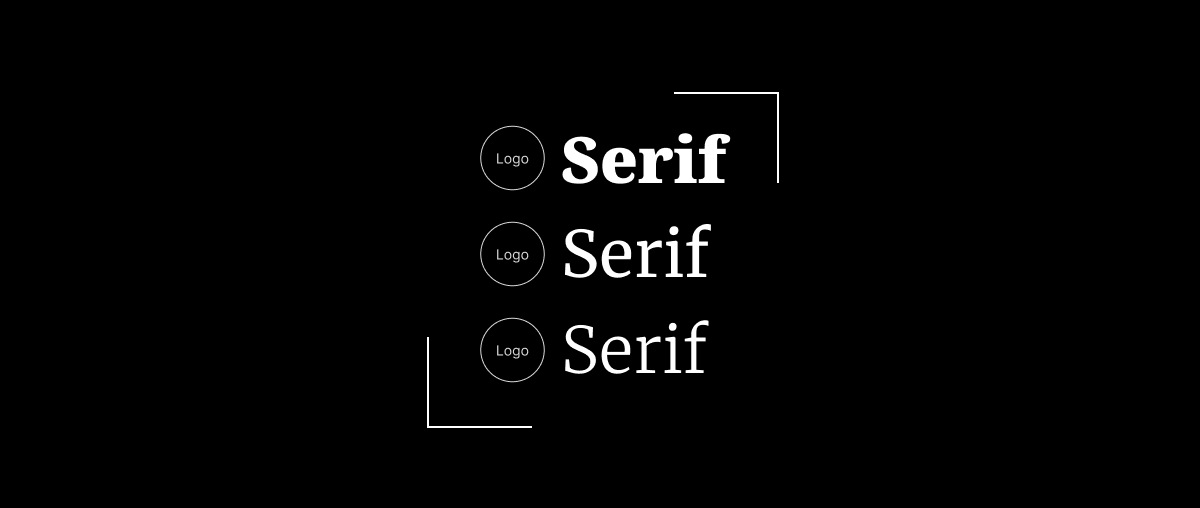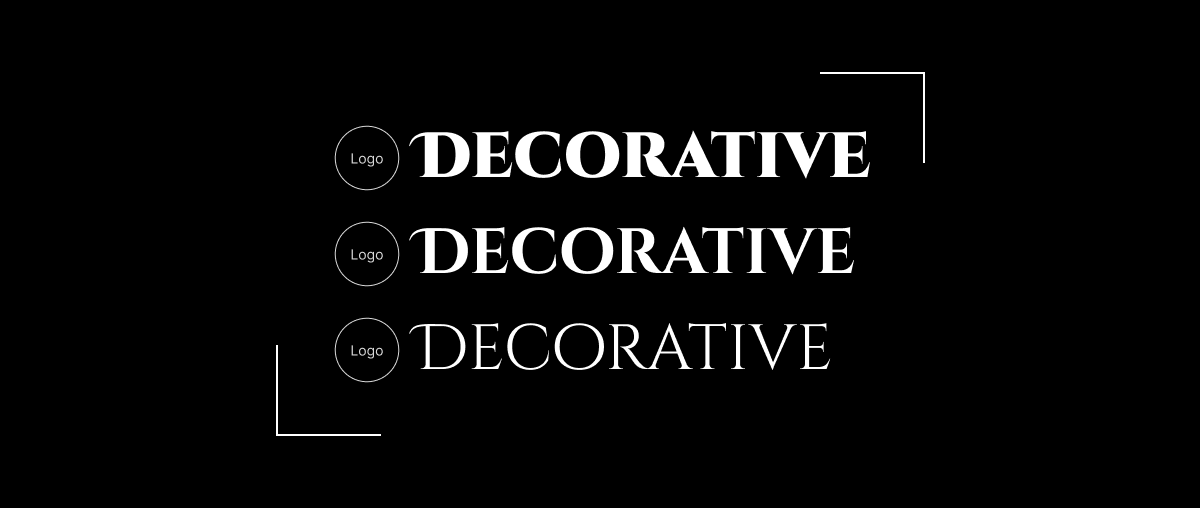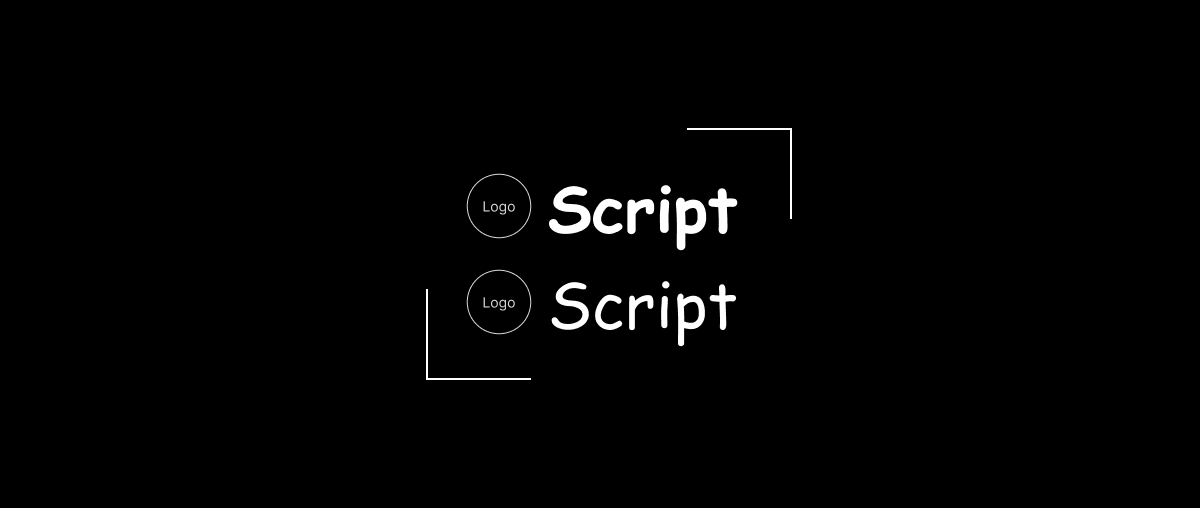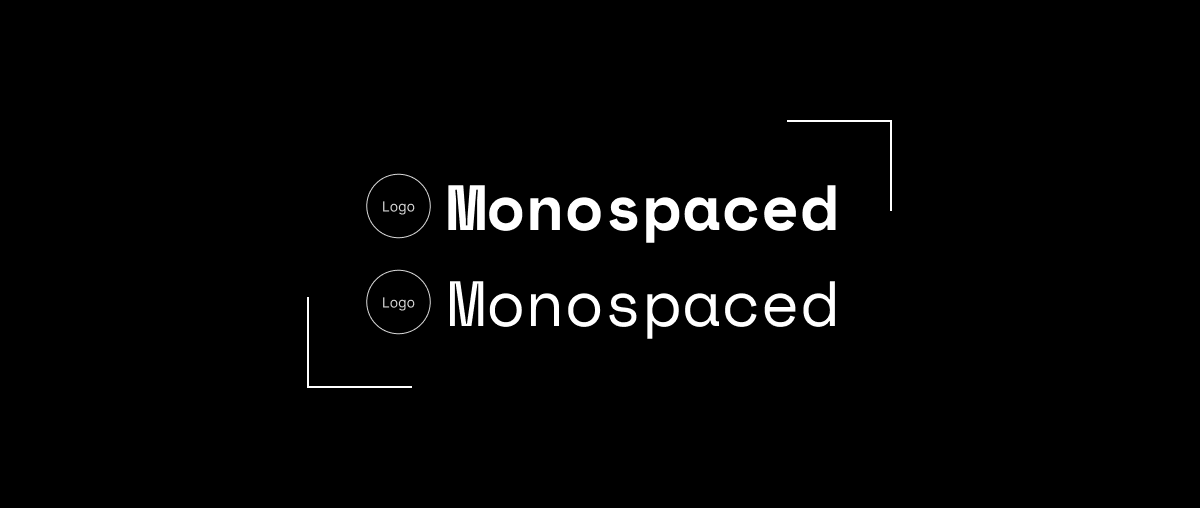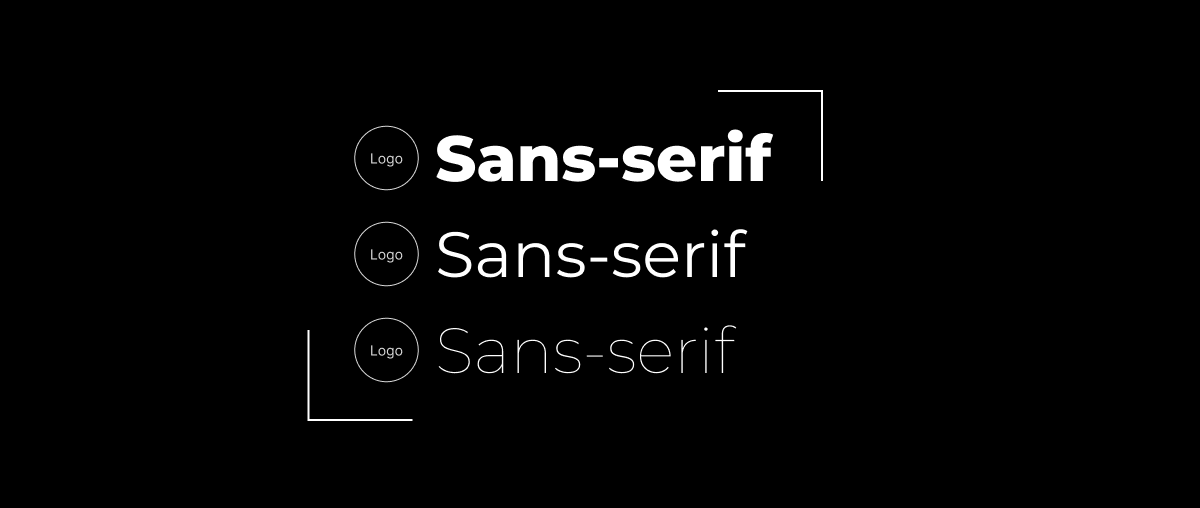
Typeface Là Gì? Những Điều Bạn Nên Biết Về Typeface
Phần lớn những người mới bắt đầu làm thiết kế đều mơ hồ về khái niệm typeface. Một kiểu chữ hoặc một tổ hợp các kiểu chữ giống nhau được gọi là typeface. Hãy cùng Terus tìm hiểu qua bài viết dưới đây.
I. Typeface là gì?
Typeface hay còn gọi là font family là một tập hợp các ký tự được thiết kế với phong cách thống nhất. Font face bao gồm các chữ cái, số, dấu chấm phẩy và các ký tự đặc biệt khác, cùng với các biến thể như chữ thường, chữ in hoa, chữ đậm, chữ nghiêng và các độ dày mỏng khác nhau.
Nó được sử dụng để tạo ra văn bản có tính thẩm mỹ và dễ đọc trong các ấn phẩm, thiết kế website và các ứng dụng khác. Typface có ý nghĩa khá rộng, bao gồm cả font vì typeface không bị hạn chế về định dạng và kích thước của chữ.
II. Tầm quan trọng của Typeface
Typeface đóng vai trò quan trọng trong thiết kế, ảnh hưởng đến nhiều khía cạnh như tính thẩm mỹ, khả năng truyền tải thông điệp, trải nghiệm người dùng và nhận diện thương hiệu. Dưới đây là một số lý do giải thích tầm quan trọng mà Terus muốn cung cấp cho bạn:
1. Truyền tải thông điệp
2. Thể hiện cá tính
3. Tạo cảm xúc
4. Hướng dẫn người đọc
5. Nhận diện thương hiệu
1. Truyền tải thông điệp
Typeface là yếu tố trực quan đầu tiên thu hút sự chú ý của người xem. Lựa chọn typeface phù hợp có thể giúp truyền tải thông điệp của bạn một cách hiệu quả. Chẳng hạn, Serif thường được sử dụng cho văn bản dài vì dễ đọc, trong khi Sans-serif phù hợp hơn cho tiêu đề và các đoạn văn bản ngắn.
2. Thể hiện cá tính
Typeface có thể thể hiện cá tính và phong cách của thiết kế. Typeface hiện đại, đơn giản có thể phù hợp cho một website công nghệ, trong khi typeface cổ điển, trang trọng có thể phù hợp hơn cho một thương hiệu cao cấp.
3. Tạo cảm xúc
Typeface có thể khơi gợi cảm xúc ở người xem. Typeface vui nhộn, sáng tạo có thể tạo cảm giác thích thú, trong khi typeface mạnh mẽ, dứt khoát có thể tạo cảm giác tin cậy.
4. Hướng dẫn người đọc
Typeface có thể được sử dụng để hướng dẫn người đọc chú ý đến những thông tin quan trọng trong thiết kế. Sử dụng typeface lớn, đậm cho tiêu đề và nhỏ hơn, thanh mảnh cho nội dung chính có thể giúp người đọc dễ dàng quét và nắm bắt thông tin.
5. Nhận diện thương hiệu
Typeface là một phần quan trọng của nhận diện thương hiệu. Lựa chọn kiểu chữ phù hợp và sử dụng nó một cách nhất quán có thể giúp tạo dựng hình ảnh thương hiệu mạnh mẽ và dễ nhận biết.
III. Một số loại Typeface
Typeface được phân loại thành các nhóm chính dựa trên đặc điểm hình dạng và tính năng của chúng. Dưới đây là một số loại phổ biến mà Terus muốn giới thiệu đến bạn:
1. Sans-serif
2. Serif
3. Script
4. Decorative
5. Mimicry
6. Monospaced
7. Fantasy Decoration
1. Sans-serif
Đây là loại chữ không có chân. Hầu hết các font chữ được sử dụng là Verdana, Arial, Tahoma, Gill Sans, Franklin Gothic, Futura và Univers. Vì nó đơn giản nên kiểu chữ này dễ nhận biết. Nhờ vào những tiến bộ đáng kể trong lĩnh vực này và sự phát triển của internet, loại chữ này đã được sử dụng khá phổ biến và rộng rãi vì nó dễ đọc, phù hợp với nhiều trường hợp và có nhiều kích thước.
Sans-serif
Sans-serif cũng được đánh giá cao vì nó có thể truyền đạt thông điệp bằng cách sử dụng các phương pháp trang trí tượng hình hoặc nhấn mạnh.
Các nhà thiết kế thường sử dụng sự đơn giản của kiểu chữ này để tạo ra một xu hướng mới giúp đảm bảo rằng tác phẩm của họ tối giản. Sự tối giản trong cách trang trí bằng kiểu chữ Sans-serif sẽ giúp tác phẩm trở nên thu hút hơn và độc đáo hơn.
2. Serif
Một loại chữ có chân được gọi là Serif. Có một số loại chữ phổ biến nhất, chẳng hạn như Times New Roman, Cambria, Book Antiqua, Georgia và Bookman, có kiểu chữ khá giống với Sans-serif ở chân và viền đỉnh của mỗi ký tự. Các nhà thiết kế chuyên nghiệp và những người sử dụng email sử dụng Serif.
Serif
Serif cũng rất tốt cho các loại văn bản trang trọng, thư từ về thương mại, thông điệp quảng cáo và các phương tiện truyền thông khác vì kiểu chữ này phổ biến và chuyên nghiệp.
Slab Serif là một font con của kiểu chữ Serif. Font này có dạng hình khối khá cứng cáp và các ký tự trong nó không bị lẫn nhau. Các dòng tiêu đề nên có kiểu chữ dày.
3. Script
Đây là kiểu chữ được tạo ra bởi các mẫu chữ viết tay. Nó thường được sử dụng trong các loại văn bản thể hiện cảm xúc của người viết hoặc giúp người đọc cảm thấy đồng cảm với họ.
Script
Các font chữ được sử dụng phổ biến trong typeface bao gồm Mistral, Comic Sans, Lucida Handwriting, Monotype, Brush Script và các font khác. Kiểu chữ này từ những kiểu chữ biết từ phấn đến những kiểu chữ nghệ thuật và tao nhã. Đây là loại chữ được sử dụng khá phổ biến để mang lại cho người xem cảm giác tinh tế và hài hước.
Văn bản trang trọng và thân mật thường có script. Tuy nhiên, kiểu chữ này không thể thể hiện được quyền lực hay uy tín của một văn bản, vì vậy chỉ nên sử dụng nó trong các văn bản mang tính tổ chức.
4. Decorative
Đây là kiểu chữ khá giống Serif vì nó có tính trang trí tự nhiên. Các nhà thiết kế thường sử dụng typeface để tạo ra các đối tượng trang trí hoặc làm điểm nhấn cho các biểu diễn của họ. Ngoài ra, kiểu chữ này rất phổ biến khi sử dụng các loại hình ảnh hoặc cảm xúc cho một số thể loại hoặc cột mốc thời gian cụ thể.
Decorative
Tuy nhiên, Terus khuyên bạn đừng sử dụng kiểu chữ này trong báo cáo kinh doanh hoặc tin tức vì nó có thể làm giảm giá trị của nội dung. Ngoài ra, bạn nên lựa chọn kỹ lưỡng khi sử dụng bất kỳ kiểu chữ nào cho không gian thiết kế.
5. Mimicry
Đây là loại chữ trang trí được tạo ra bằng cách nhái lại các loại chữ khác nhau. Tiếng Trung, tiếng Hàn và tiếng Ấn là những ví dụ. Cảm giác ngoại ngữ trong thiết kế thường được tạo ra bằng cách sử dụng các loại chữ này.
6. Monospaced
Đây là kiểu chữ có độ rộng của các con chữ bằng nhau, mang lại cảm giác đều đặn và mũm mĩm. Nó cũng mang lại cảm giác khá hay ho. Monospace và lucida là những ví dụ về font chữ này.
Monospaced
7. Fantasy Decoration
Đây có thể được coi là kiểu chữ có hình thù đặc biệt nhất vì nó thường có hình dạng như con người, đồ vật, nhân vật hoạt hình hoặc hoa văn.
IV. Cách sử dụng typeface phù hợp
Typeface đóng vai trò quan trọng trong thiết kế, ảnh hưởng đến tính thẩm mỹ, khả năng truyền tải thông điệp và trải nghiệm người dùng. Sử dụng kiểu chữ đúng cách giúp bạn tạo ra những thiết kế đẹp mắt, thu hút và hiệu quả. Terus sẽ mang đến cho bạn một số nguyên tắc cơ bản để sử dụng hiệu quả:
1. Lựa chọn typeface phù hợp
2. Sử dụng tối đa 2-3 typeface trong cùng một thiết kế
3. Sử dụng các biến thể của typeface
4. Chú ý đến khoảng cách và bố cục
5. Sử dụng typeface chất lượng cao
6. Kiểm tra typeface trên nhiều thiết bị
7. Cập nhật xu hướng typeface
1. Lựa chọn typeface phù hợp
Xác định mục đích sử dụng: Bạn muốn thiết kế gì? Website, áp phích, logo, sách báo? Mục đích sử dụng sẽ ảnh hưởng đến loại typeface phù hợp.
Xác định đối tượng mục tiêu: Ai là người sẽ xem thiết kế của bạn? Độ tuổi, sở thích, trình độ của họ là gì? Hiểu rõ đối tượng mục tiêu giúp bạn chọn typeface phù hợp với thị hiếu và khả năng tiếp nhận của họ.
Xác định thông điệp muốn truyền tải: Bạn muốn truyền tải thông điệp gì qua thiết kế? Thông điệp vui nhộn, trang trọng, hay hiện đại? Lựa chọn typeface phù hợp với thông điệp sẽ giúp tăng hiệu quả truyền tải.
2. Sử dụng tối đa 2-3 typeface trong cùng một thiết kế
Việc sử dụng quá nhiều typeface có thể khiến thiết kế trở nên rối mắt và khó đọc. Nên sử dụng tối đa 2-3 loại cho một thiết kế, kết hợp hài hòa để tạo sự cân bằng và thống nhất.
3. Sử dụng các biến thể của typeface
Hầu hết các typeface đều có các biến thể như chữ thường, chữ in hoa, chữ đậm, chữ nghiêng và các độ dày mỏng khác nhau. Sử dụng các biến thể này một cách hợp lý giúp tạo điểm nhấn, phân chia cấp bậc thông tin và tăng hiệu quả đọc.
4. Chú ý đến khoảng cách và bố cục
Khoảng cách giữa các ký tự, giữa các dòng chữ và khoảng cách lề trang ảnh hưởng đến khả năng đọc và tính thẩm mỹ của thiết kế. Hãy đảm bảo các khoảng cách được sắp xếp hợp lý, tạo sự thoải mái cho mắt người đọc.
5. Sử dụng typeface chất lượng cao
Sử dụng typeface chất lượng cao giúp đảm bảo hình ảnh rõ nét, không bị vỡ hoặc biến dạng. Tránh sử dụng kiểu chữ miễn phí có chất lượng thấp hoặc không rõ nguồn gốc.
6. Kiểm tra typeface trên nhiều thiết bị
Thiết kế của bạn sẽ được hiển thị trên nhiều thiết bị khác nhau như máy tính, điện thoại, máy tính bảng. Hãy kiểm tra typeface trên nhiều thiết bị để đảm bảo hiển thị chính xác và đẹp mắt trên mọi màn hình.
Kiểm tra typeface trên nhiều thiết bị
7. Cập nhật xu hướng typeface
Ngành thiết kế luôn thay đổi và phát triển. Hãy cập nhật xu hướng typeface mới để tạo ra những thiết kế hiện đại và thu hút.
Nhìn chung, Typeface là một công cụ thiết kế mạnh mẽ có thể giúp bạn truyền tải thông điệp, thể hiện cá tính, tạo cảm xúc, hướng dẫn người đọc và xây dựng nhận diện thương hiệu. Hãy dành thời gian để tìm hiểu về các loại typeface khác nhau và sử dụng chúng một cách hiệu quả để tạo ra những thiết kế đẹp mắt, thu hút và truyền tải thông điệp hiệu quả.
V. Tổng kết
Bài viết là các thông tin về Typeface và những điều bạn nên biết về Typeface mà Terus muốn gửi đến cho quý đơn vị đang hợp tác đến Terus và bạn bè doanh nghiệp của Terus.
Hi vọng bài viết có thể giúp ích được cho bạn, cảm ơn bạn đã đọc hết bài viết.
Nếu bạn có bất cứ yêu cầu gì về Terus có thể liên hệ tại đây nhé!
Theo dõi Terus tại:
FAQ – Giải đáp thắc mắc về Typeface
1. Làm thế nào để kết hợp nhiều typeface trong một thiết kế mà vẫn đảm bảo tính thẩm mỹ?
Việc kết hợp nhiều typeface có thể tạo điểm nhấn và sự đa dạng cho thiết kế. Tuy nhiên Terus muốn lưu ý rằng một số nguyên tắc để đảm bảo tính thẩm mỹ:
• Chọn typeface có cùng phong cách hoặc tương đồng nhau.
• Sử dụng tỷ lệ phân cấp: Sử dụng kiểu chữ có kích thước và độ dày mỏng khác nhau để tạo điểm nhấn và phân chia cấp bậc thông tin.
• Hạn chế số lượng: Nên sử dụng tối đa 2-3 typeface trong cùng một thiết kế để tránh gây rối mắt.
• Chú ý đến màu sắc: Sử dụng màu sắc phù hợp để tạo sự hài hòa giữa các.
2. Nên sử dụng typeface nào cho logo?
Lựa chọn typeface cho logo phụ thuộc vào nhiều yếu tố như ngành nghề, đối tượng mục tiêu, thông điệp thương hiệu. Tuy nhiên, ở phần này Terus cũng có một số lưu ý chung khi chọn typeface cho logo:
• Đơn giản, dễ đọc: Logo cần dễ đọc và ghi nhớ, tránh sử dụng typeface quá phức tạp hoặc cầu kỳ.
• Phù hợp với ngành nghề: Serif có thể phù hợp cho thương hiệu luật sư, trong khi Sans-serif phù hợp cho thương hiệu công nghệ.
• Thể hiện cá tính thương hiệu: Logo cần thể hiện được cá tính và thông điệp của thương hiệu.
• Dễ ứng dụng: Logo cần dễ ứng dụng trên nhiều phương tiện khác nhau như in ấn, website, mạng xã hội.
3. Xu hướng typeface nào đang thịnh hành trong thiết kế hiện nay?
Dưới đây, Terus sẽ giới thiệu đến bạn một số xu hướng typeface phổ biến hiện nay:
• Sans-serif hiện đại: Loại này đơn giản, dễ đọc và phù hợp với thiết kế website và giao diện ứng dụng.
• Serif cổ điển: Loại này mang lại cảm giác sang trọng, tinh tế và có thể phù hợp cho logo hoặc ấn phẩm cao cấp.
• Viết tay: Loại này tạo cảm giác gần gũi, thân thiện và có thể phù hợp cho thương hiệu hướng đến đối tượng trẻ.
• Vui nhộn, sáng tạo: Loại này thu hút sự chú ý và có thể phù hợp cho thương hiệu muốn thể hiện sự trẻ trung, năng động.
4. Sự khác biệt giữa Typeface và Font?
Typeface là thiết kế tổng thể của một tập hợp ký tự, bao gồm các yếu tố như kiểu dáng, đường nét, tỷ lệ và khoảng cách giữa các ký tự.
Font là một tập tin kỹ thuật số chứa các ký tự của một typeface ở một định dạng cụ thể, ví dụ như TrueType OpenType (OTF), Web Open Font Format (WOFF) hoặc Scalable Vector Graphics (SVG).
5. Các yếu tố nào ảnh hưởng đến xu hướng typeface?
Như Terus đã đề cập ở phía trên, xu hướng typeface thay đổi theo thời gian, chịu ảnh hưởng bởi nhiều yếu tố. Sau đây, Terus sẽ liệu kê các yếu tố ảnh hưởng để giúp bạn có thể nắm rõ hơn:
• Công nghệ: Xuất hiện công nghệ mới, màn hình độ phân giải cao dẫn đến kiểu chữ mảnh mai, sắc nét hơn. Phát triển website, ứng dụng di động đòi hỏi phù hợp hiển thị trên nhiều kích thước màn hình.
• Văn hóa: Xu hướng xã hội, văn hóa ảnh hưởng đến sở thích thẩm mỹ. Xu hướng hoài cổ ưa chuộng typeface cổ điển, trong khi xu hướng hiện đại ưa chuộng typeface tối giản.
• Thiết kế: Xu hướng thiết kế chung ảnh hưởng đến phong cách. Xu hướng tối giản ưa chuộng Sans-serif đơn giản, trong khi xu hướng retro ưa chuộng Serif thanh lịch.
• Thương hiệu: Các thương hiệu lớn sử dụng typeface độc đáo để tạo dựng hình ảnh thương hiệu riêng biệt. Xu hướng này ảnh hưởng đến thị hiếu chung của người dùng và nhà thiết kế.
• Tâm lý học: Các nhà nghiên cứu chỉ ra rằng typeface có thể ảnh hưởng đến cảm xúc và hành vi của người dùng. Typeface vui nhộn thu hút trẻ em, typeface trang trọng tạo cảm giác tin cậy.